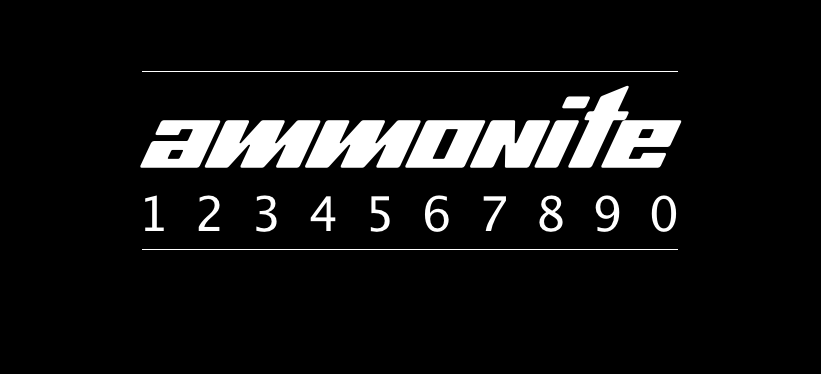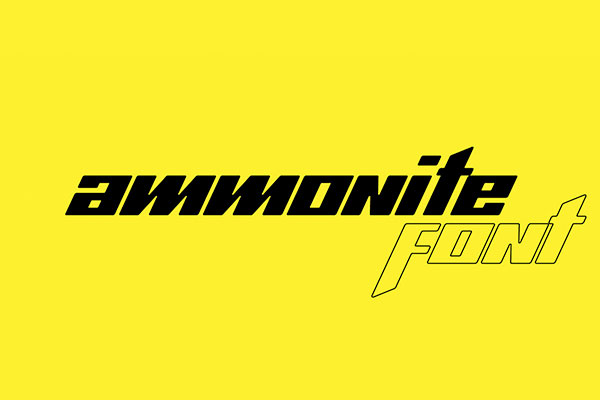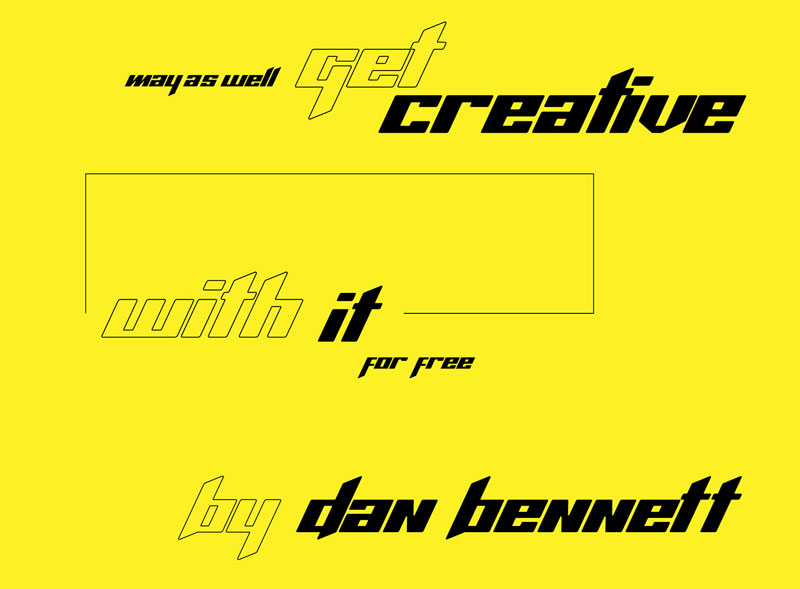
Ammonite
Ammonite是英国设计师Daniel Bennett创作的一款英文字体,该字体有一定的倾斜角度,适合富有速度、动感和激情的场合使用,用来做大标题也很不错!
由于该字体不是等宽字体,所以使用的时候,可能需要手动调整字体的间距;此外该字体未包含数字的设计,英文字符部分也仅支持小写英文字符,使用的时候需要注意。